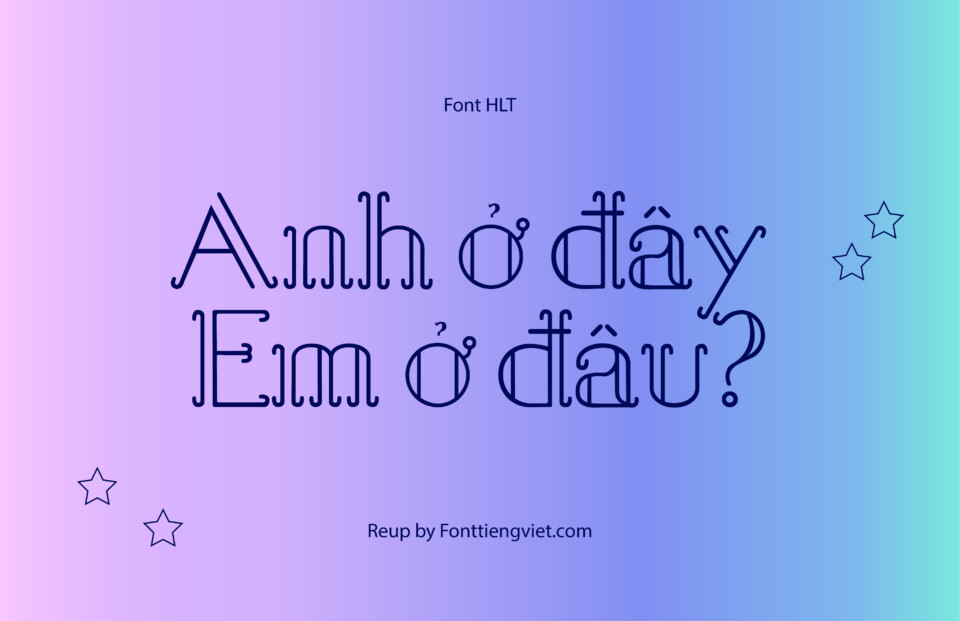
Font Việt hóa HLT Sail Away
Giới thiệu về bộ Font Việt hóa HLT Sail Away
Trong thế giới đồ họa hiện đại, việc lựa chọn Font Miễn Phí phù hợp đóng vai trò quyết định đến sự thành công của một tác phẩm. Font Việt hóa HLT Sail Away là một trong những bộ phông chữ mang phong cách phóng khoáng, tự do và vô cùng tinh tế. Được chuyển ngữ bởi đội ngũ HLT, bộ font này đã khắc phục hoàn toàn lỗi dấu tiếng Việt, giúp người dùng tại Việt Nam dễ dàng ứng dụng vào các phần mềm thiết kế như Photoshop hay Canva. Với các đường nét thanh mảnh nhưng chắc chắn, Font Việt hóa HLT Sail Away mang lại cảm giác nhẹ nhàng như những cánh buồm trên biển cả mênh mông.
Tại sao nên sử dụng Font Việt hóa HLT Sail Away?
Bộ font này không chỉ đẹp về mặt thẩm mỹ mà còn sở hữu tính linh hoạt cao. Font Việt hóa HLT Sail Away rất phù hợp cho các dự án thiết kế bìa sách, thiệp mời, hoặc các poster quảng cáo cần sự mềm mại. Đối với các bạn học sinh và giáo viên, phông chữ này giúp các bài thuyết trình trở nên sinh động và thu hút hơn bao giờ hết. Hệ thống ký tự được tối ưu hóa giúp việc soạn thảo văn bản trở nên trôi chảy, không bị gãy nét hay sai lệch định dạng. Đây thực sự là lựa chọn hoàn hảo cho những ai yêu thích phong cách tối giản nhưng vẫn đầy cá tính.
Cách ứng dụng Font Việt hóa HLT Sail Away hiệu quả
Lưu ý khi phối màu và bố cục
Khi sử dụng Font Việt hóa HLT Sail Away, bạn nên ưu tiên các tông màu pastel hoặc màu trung tính để làm nổi bật nét vẽ thanh lịch của chữ. Việc kết hợp với các hình ảnh thiên nhiên sẽ tạo nên một tổng thể hài hòa và chuyên nghiệp. Đừng ngần ngại thử nghiệm bộ font này trong các tiêu đề lớn để tạo điểm nhấn thị giác mạnh mẽ cho người xem.
Kết luận về bộ phông chữ độc đáo